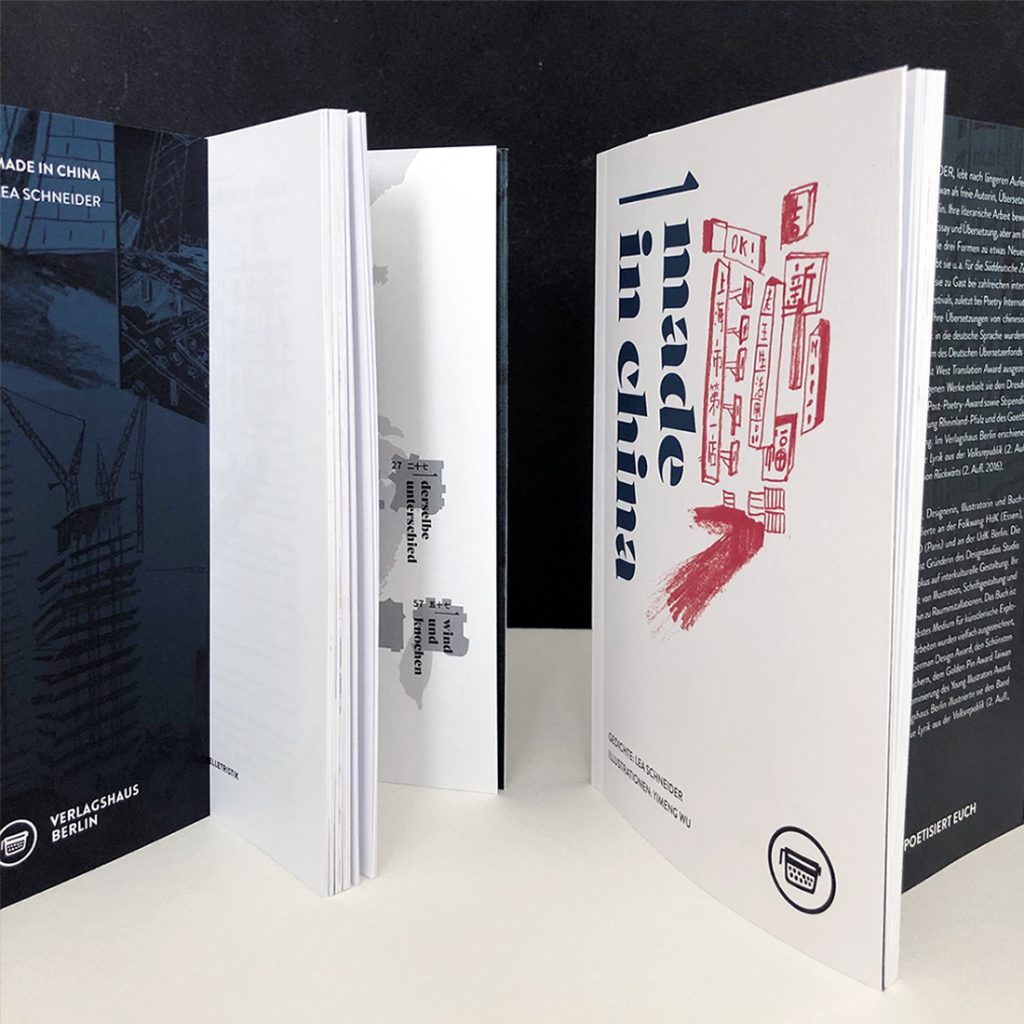
Für das Verlagshaus Berlin habe ich den Band Kreuzfällen. Ein Epyllion gestaltet. Es ist ein witziges Langgedicht, dass die fiktive Geschichte des Kreuzefällens in den Alpen erzählt. Die beiden Autoren Tobias Roth & Daniel Bayerstorfer gehen in dem Text der Frage nach: Was wäre, wenn man Gipfelkreuze einfach absägte? In einer poetisch-wilden Wanderung durch die Alpen fragen sie nach Mythen und Geschichten, die wir in Landschaften eingeschrieben haben. Das Buch ist kein nostalgischer Ruf nach unberührter Natur, sondern ein Plädoyer für den bewussten Umgang mit Natur und eine neue Kulturgeschichte der Symbole.
Zum Text entwickelte ich doppelseitige, schwarz-weiße Tuschezeichnungen. Fragmentarische naturhafte Strukturen verbinden sich mit konkreten Pflanzendarstellungen und erzeugen Brüche zu den oppulenten Naturbeschreibungen. »Kreuzfällen« ist als Hardcover in ein mattes Werkdruckpapier eingefasst, mit schwarzem Vorsatzpapier, Kapitelband und Lesebändchen ausgestattet und typografisch-verliebt in den Schriften »Poplar« und Elza« gesetzt.
Kreuzfällen. Ein Epyllion
Langgedicht: Tobias Roth & Daniel Bayerstorfer
Zeichnungen: Andrea Schmidt
Vor dem Hintergrund des 7. Oktober und des darauf folgenden Krieges ist The In-Between / Das Dazwischen von Sandra Gugić, Lily Shehady und Sarah Sassoon ein Buch, das schmerzhafte Fragen stellt, den Alltag zwischen Angst, Verwirrung, Resignation und Hoffnung beschreibt und an die Menschlichkeit appelliert. In ihrem gemeinsamen Schreiben schaffen Sandra Gugić, Lily Shehady und Sarah Sassoon inmitten von Chaos und Zerstörung einen Raum der Solidarität, der Empathie, des Verständnisses und der Stärkung.
Das 160-Seiten-starke Kippbuch kann von beiden Seiten gelesen werden – entweder im englischen Original oder ins Deutsche übertragen von Jo Frank. Die ausgewogen-opulente Gestaltung von Andrea Schmidt spiegelt das Dazwischen wieder: weißer und schwarzer Druck auf stormy-grey Papier, versehen mit feinen Strichzeichnungen von Oliver Hummel.
The In-Between / Das Dazwischen
Gedichte und lyrische Essays: Sandra Gugić, Lily Shehady und Sarah Sassoon
Übersetzung: Jo Frank, Zeichnungen: Oliver Hummel
Seit Anfang des Jahres hat mich die Gestaltung der Doppelpublikation »Am Ende der Weißheit / Verschalte Verbindungen« von Swantje Lichtenstein begleitet – zwei Bücher einer Lyrikerin, die in ihrer Arbeit die Schnittstellen von Wissenschaft, poetischer Praxis, performativer Gestaltung und Gesellschaftskritik ausleuchtet. Der Band ist jetzt endlich bei uns Verlagshaus Berlin erschienen und wurde Anfang Juli im »Ocelot, not just another Bookstore« vorgestellt.
»Am Ende der Weißheit« untersucht die komplexe Vielfalt der rassistischen Idee des Weißseins und des Weißen Wissens. Weißheit wird angezeigt, aufgefächert und seziert. Es ist ein Buch gegen das Vonsichweisen und für das Bezeugen von ganz alltäglichen Rassismen – und nicht zuletzt ein Einstehen für Poesie als widerständige Literatur. In dem zweiten Band »Verschalte Verbindungen« wird Poesie zum Gestaltwandlungsprozess, der Verschwiegenes zur Sprache bringt, Verbotenes benennt, Gestohlenes freisetzt und sich nicht zufrieden gibt mit den besetzten, übernommenen, verletzten Sprachen. Basis ihrer Auseinandersetzung ist ein performatives Verständnis des Schreibens: in Buchform übersetzt bedeutet das ein stetiges Ausloten der Grenzen der Sprache und des Sprechens.
Die Gestaltung der Doppelpublikation stellt sich mit dem Inhalt auf: durch farbverlaufende Umschläge, eine schwere Type, Fedrigoni-Papiere in verschiedenen Weiß-tönungen und einen schwarz-durchgefärbten Papp-Schuber mit ausgestanzter verbindender ß-Ligatur, die Inhalt und Form, Vergangenheit und Gegenwart engführt. Nicht nur inhaltlich sondern auch optisch ein grandios schönes Buch!
Am Ende der Weißheit / Verschalte Verbindungen
Doppelpublikation von Swantje Lichtenstein
Gestaltet wurde das Buch von Typografie/im/Kontext.
Podcast »BookGazette« // Juni 2021
Mit Nick Lüthi, dem Initiator von bookgazette.xyz habe ich mich in dem Podcast »BookGazette. Die Welt der unabhängigen Verlage« über Lyrik, Ligaturen & Typografie unterhalten. Wir sprachen über unabhängiges Verlegen, warum man vor Gedichten keine Angst haben sollte und wie Gestaltung & Inhalt in einem Buch zusammen gehen können. Im Übrigen sind alle Folgen des Podcasts super spannend, denn es kommen Expert*innen aus ganz unterschiedlichen Bereichen des unabhängigen Verlegens zu Wort und sprechen über ihre jeweiligen Erfahrungen – sehr individuell, inspirierend und professionell. Große Empfehlung!
Essay & Editorial Design // Dietz Verlag // August 2020
Von Franziska Richter, der Herausgeberin der Anthologie »Echoräume des Schocks« wurde ich neben vielen anderen Kreativen und Kulturschaffenden eingeladen, einen Text zur Anthologie über die Zeit des Lockdown beizusteuern. Entstanden ist der Essay »Ich glaube an die Chance, die in Vagheit liegt«, der persönliche Erfahrungen in meinen Rollen als Verlegerin, Typografin und Lehrende in einer Zeit großer Unsicherheiten reflektiert. Den Essay könnt ihr ab Seite 66 direkt im Buch nachlesen.
Die Studierenden setzten sich neben dem Erlernen handwerklicher Grundlagen der typografischen Gestaltung mit Schrift und Zeichenfamilien unterschiedlicher Kulturen auch mit neuen Anforderungen des modernen multilingualen Grafikdesigns auseinander.